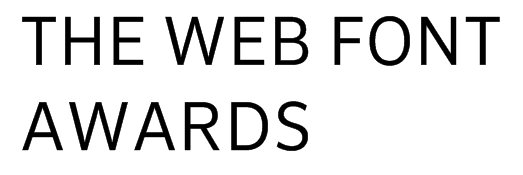
Schrift des »Web Font Awards« gesucht
weiß jemand welche Schrift für das Logo des »Web Font Awards« verwendet wurde? Dachte kurz an die Interstate, aber die ist es doch nicht.
Jemand ne Idee?
FF Sero könnte es sein …
Vielleicht wurde am O noch etwas gezupft. Oder es ist doch eine andere :-)
Ich habe auch gesucht und fand es echt schwierig. Die Avenir war (wie bei Uwe) das dichteste, was ich gefunden habe, allerdings passen da R und D nicht richtig. Logos mit dem Word AWARD in Versalien sind übrigens sowieso kniffelig, finde ich. Meistens sieht die Kombination »AWA« blöd aus. Ich habe bei einem Award-Logo mal die Buchstaben A und W komplett überarbeitet, um ein harmonisches Ergebnis hinzubekommen. :-)
habe ich noch einen Versuch? Bitte? Ich habe Bertels Bildchen einfach mal Whatfontis
http://www.whatfontis.com/ verfüttert und geschaut was das raus kommt. Das naheliegenste scheint die „Slate“ von Rod McDonald (2006), siehe http://www.identifont.com/show?IO7
Durch die ähnlichen Schriften auf Identifont habe ich mich aber nicht geklickt, da könnte noch der eine oder andere Kandidat zu finden sein.
Typo :-(
Tatsache, die »Slate« ist es. Im Schnitt »Book«. Kannte die bisher nicht, finde aber sie ist ganz schön anzuschauen.
… Ich habe Bertels Bildchen einfach mal Whatfontis verfüttert
Bitte aber bedenken, dass mein Bildchen in der FF Sero gesetzt ist.
@ bertel: Witzig, dass das zum richtigen Ergebnis geführt hat. Aber whatfontis spuckt auch die »Corporate S« als Ergebnis aus, wenn man ein Bild der »Slate« hochläd!? ;)
@ Ralf: Findest Du? Find ich gar nicht. Die »Frutiger« ist doch so humanistisch, die »Slate« dagegen wirkt so kühl und konstruiert.
Edit: Oder meintest Du eher, dass sie Adrian Frutiger schreit? :)
Wobei die irgendwie aus jeder Pore Fruuuuh-tieeee-geeeer zu schreien scheint.
Du meintest sicher Avenir? Die Schrift schreit einfach nach Avenir und ein bisschen nach Adrian Frutiger.
Bitte aber bedenken, dass mein Bildchen in der FF Sero gesetzt ist.
Ja, das ist ja das Nette an diesen Maschinchen. Du wirfst eine sehr ähnliche Schrift zum Fraß vor und bekommst dann ganz viele dazu ähnliche Schriften. In vielen Fällen ist dann die gesuchte Schrift dabei.
Ich wollte damit sagen, dass ich bereits eine ähnliche Schrift gepostet habe. Wenn du jetzt die ähnliche als Basis nimmst, entfernst du dich noch weiter von der gesuchten.
Ich? :shock:
Ich hab das jetzt mal mit dem Linotype-FontIdentifier probiert, da kam aber auch nichts raus.
Ist wohl eine Ableitung. Oder nicht von Linotype ;-)
Oder aber Du landest aus Versehen einen Volltreffer. ;-)
*Hüstel* Das hat absolut nix mit Versehen zu tun. Die Wahrscheinlichkeit das WhatFontis unter den 100 Vorschlägen aus der eigenen Datenbank auch die gewünschte Schrift findet ist recht hoch. Es klappt doch erstaunlich gut bei zu schlecht aufgelösten Beispielgrafiken eine sehr ähnliche Schrift in einer besser aufgelösten Grafik zu verfüttern und dann in den Ergebnissen nach der Richtigen zu suchen.